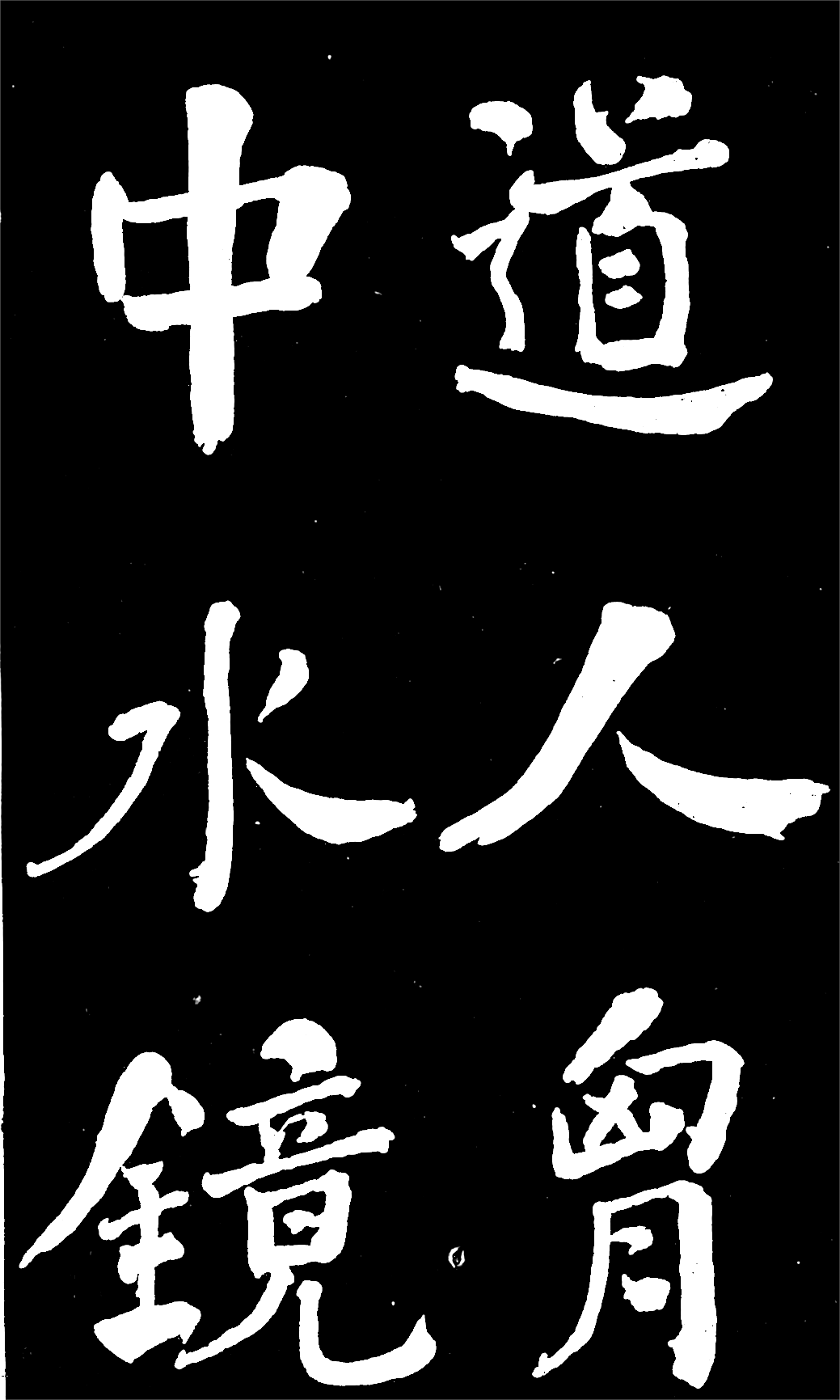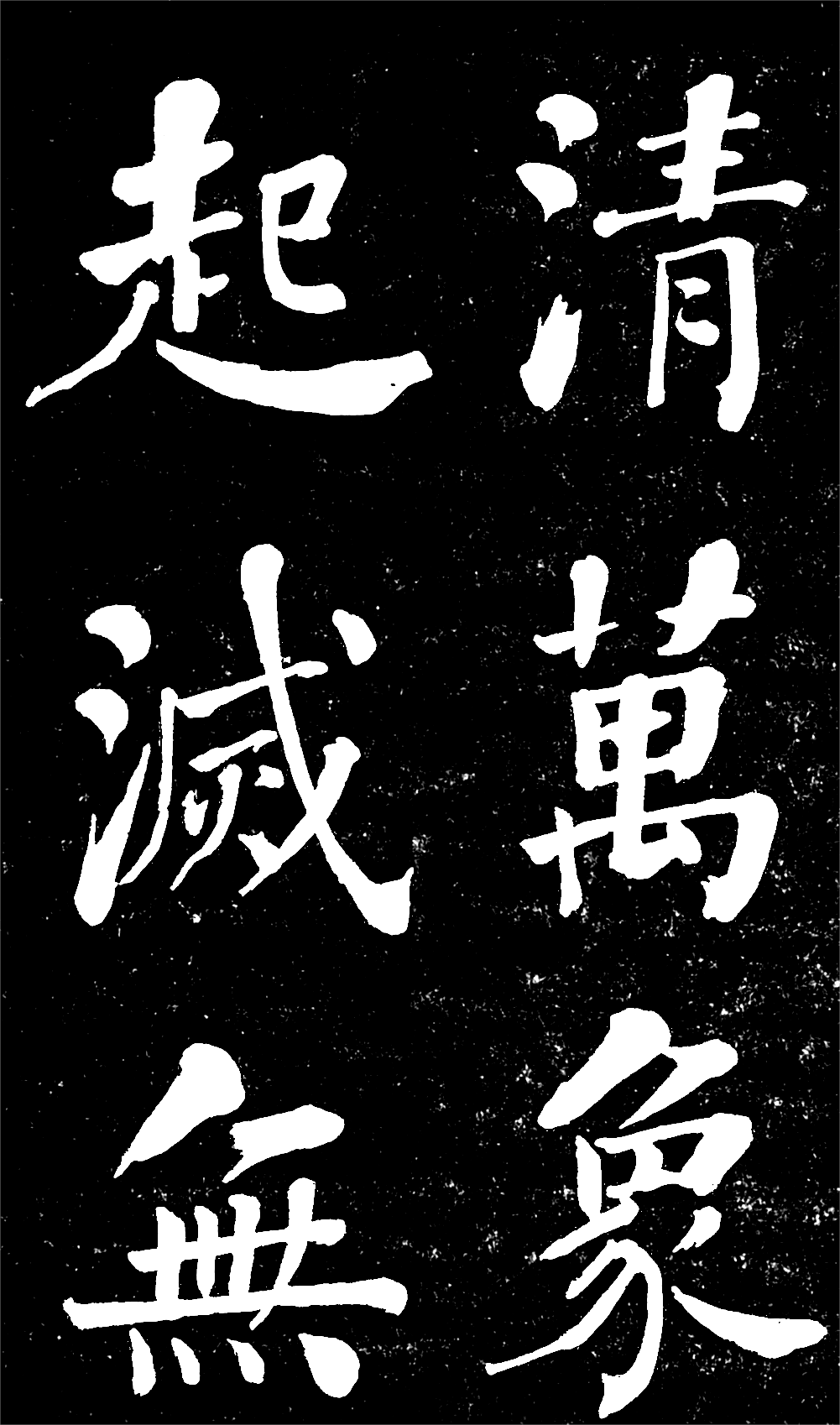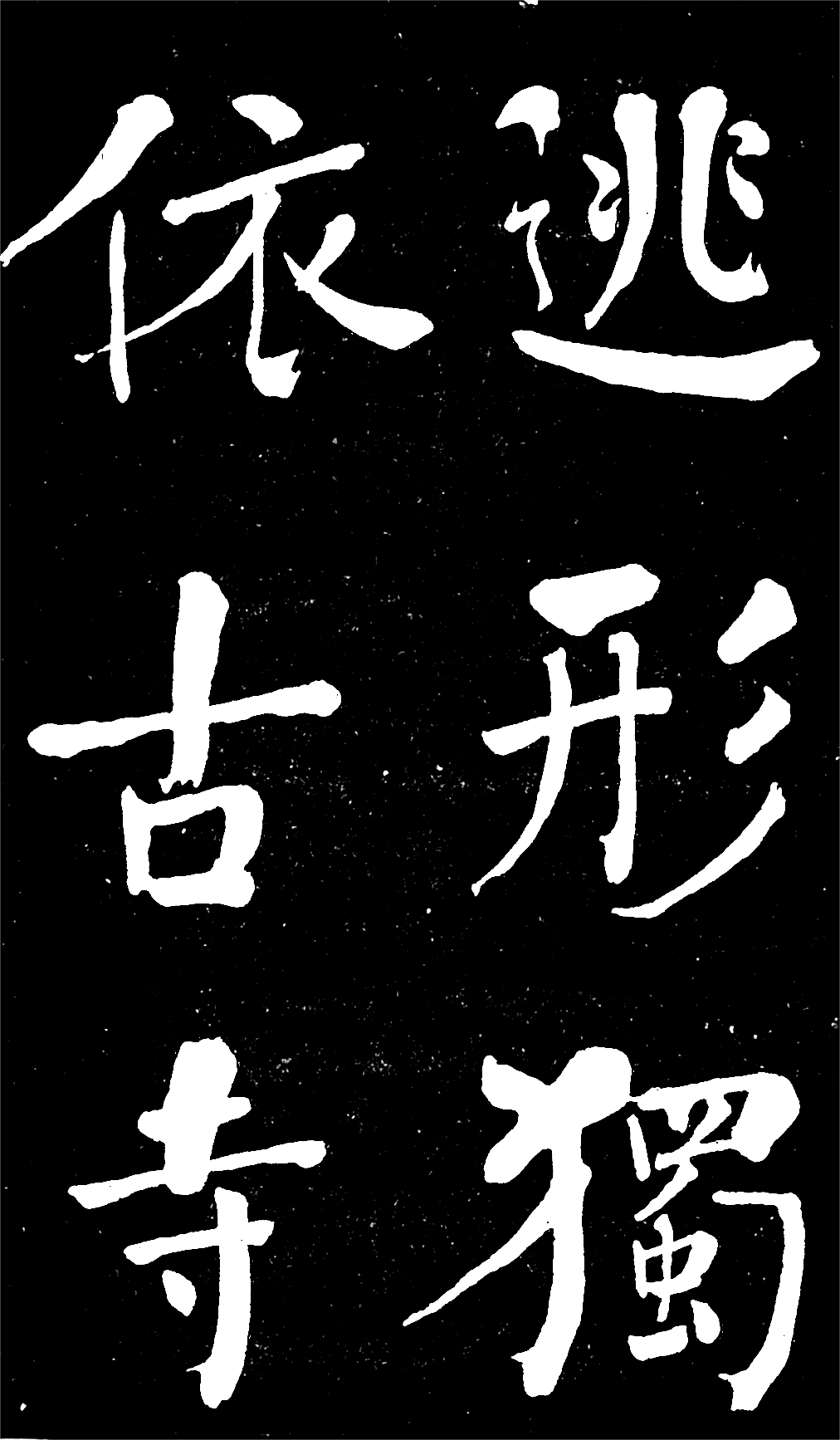
字体全名: 汉标何绍基东坡诗册拓版
铸字厂: 真迹小字库
字体简介: 下载须知:本字库非标准GB2312字库。本字库只包含了《东坡诗册》真迹上的“286个字”。详见图样。 清代书法家何绍基楷书欣赏《东坡诗册》。何绍基(1799-1873),字子贞,号东洲、晚年又号蝯叟。今湖南道县人,清代晚期著名的诗人、书法家,道光年间的进士。何绍基是何绍基的书法,早年由颜真卿,欧阳通入手,上追秦汉篆隶,自成一家。中年潜心临摹魏碑,他用自创的回腕法书写,字体充满了极强的个性;晚年他专攻篆隶,这使他的书法更增添了雄浑之气。何绍基将书法中的“行、草、隶、篆”融为一体,写出的字出神入化。